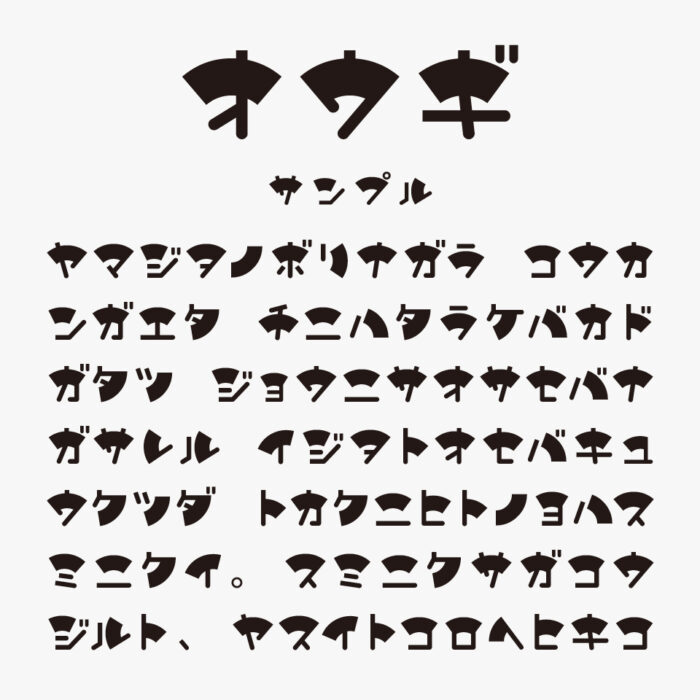
IKオウギフォントは、扇(おうぎ)をモチーフとした和風で個性的なデザインが際立つカタカナフォントです。
カタカナの一部に“扇”を思わせる半円状のパーツがあしらわれた他のフォントにはないユニークな遊び心を感じるフォントです。視認性よりも装飾性に重きを置いたスタイルで、タイトルやロゴにぴったりです。
IKオウギ
収録文字は、カタカナが収録されています。
ひらがな×
カタカナ○
漢字×